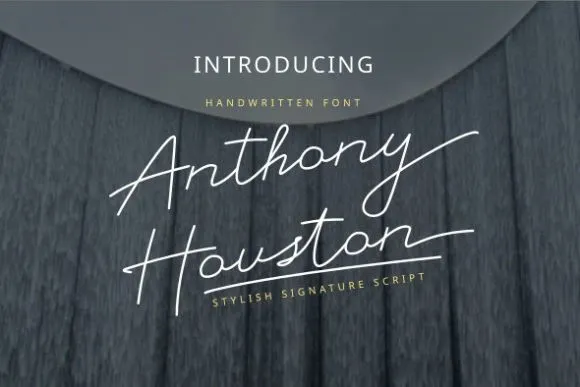
Anthony Houston Font – Download Grátis
Este tipo de letra é uma tipografia de script monolínea que apresenta um aspecto muito natural, suave e levemente fino. Com sua aparência elegante e moderna, esta fonte se destaca para ser usada em diversos ambientes de design. Seja ela um elemento chave para logos, criação de marca, convites, encomendas, designs de casamentos ou até postagens no social media, essa tipografia atende a uma ampla gama de necessidades de design. O estilo elegante e moderno da fonte “Anthony Houston Font” faz dela uma opção irresistível para quem busca um equilíbrio entre simplicidade e sofisticação em seu trabalho gráfico.